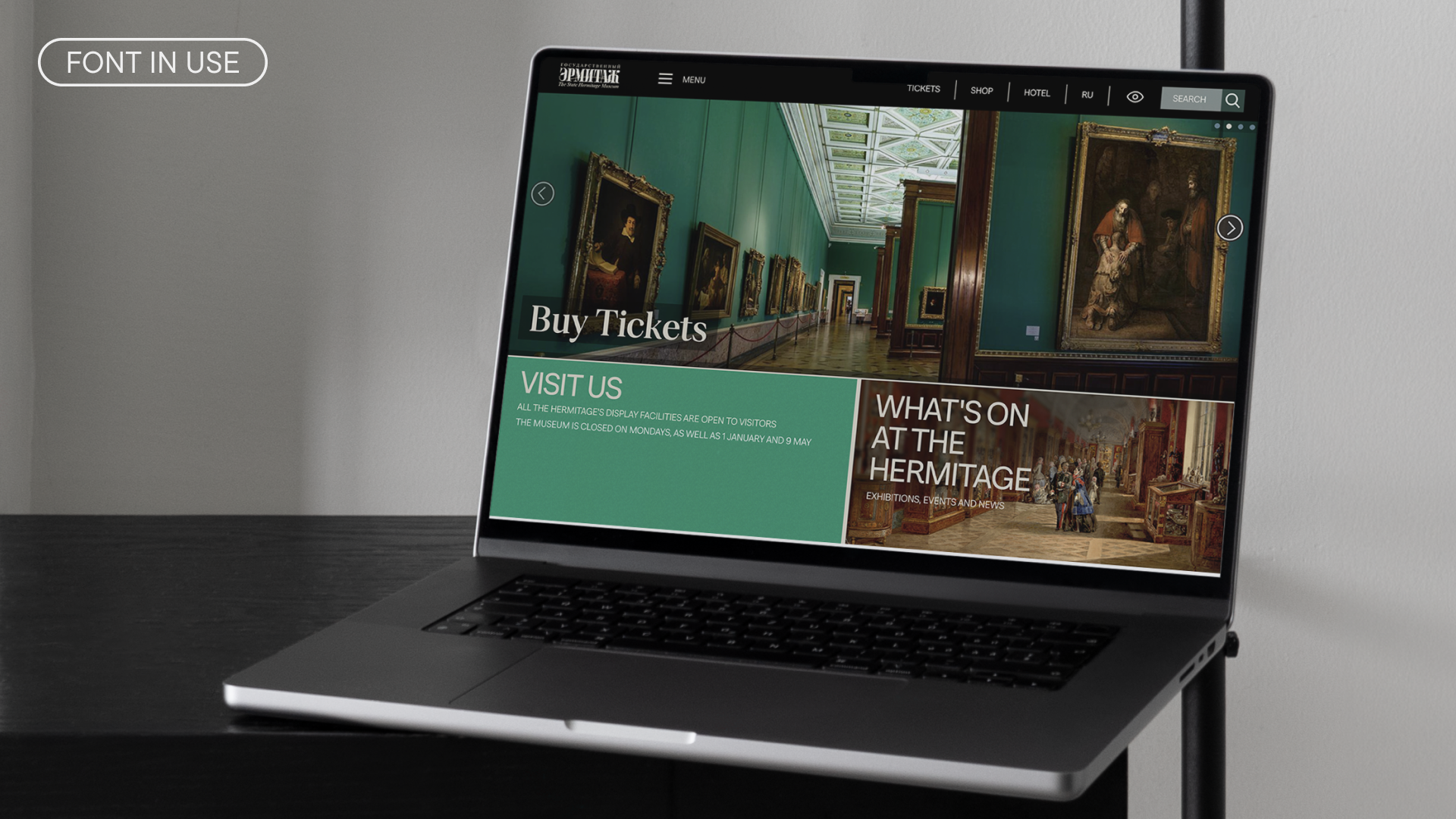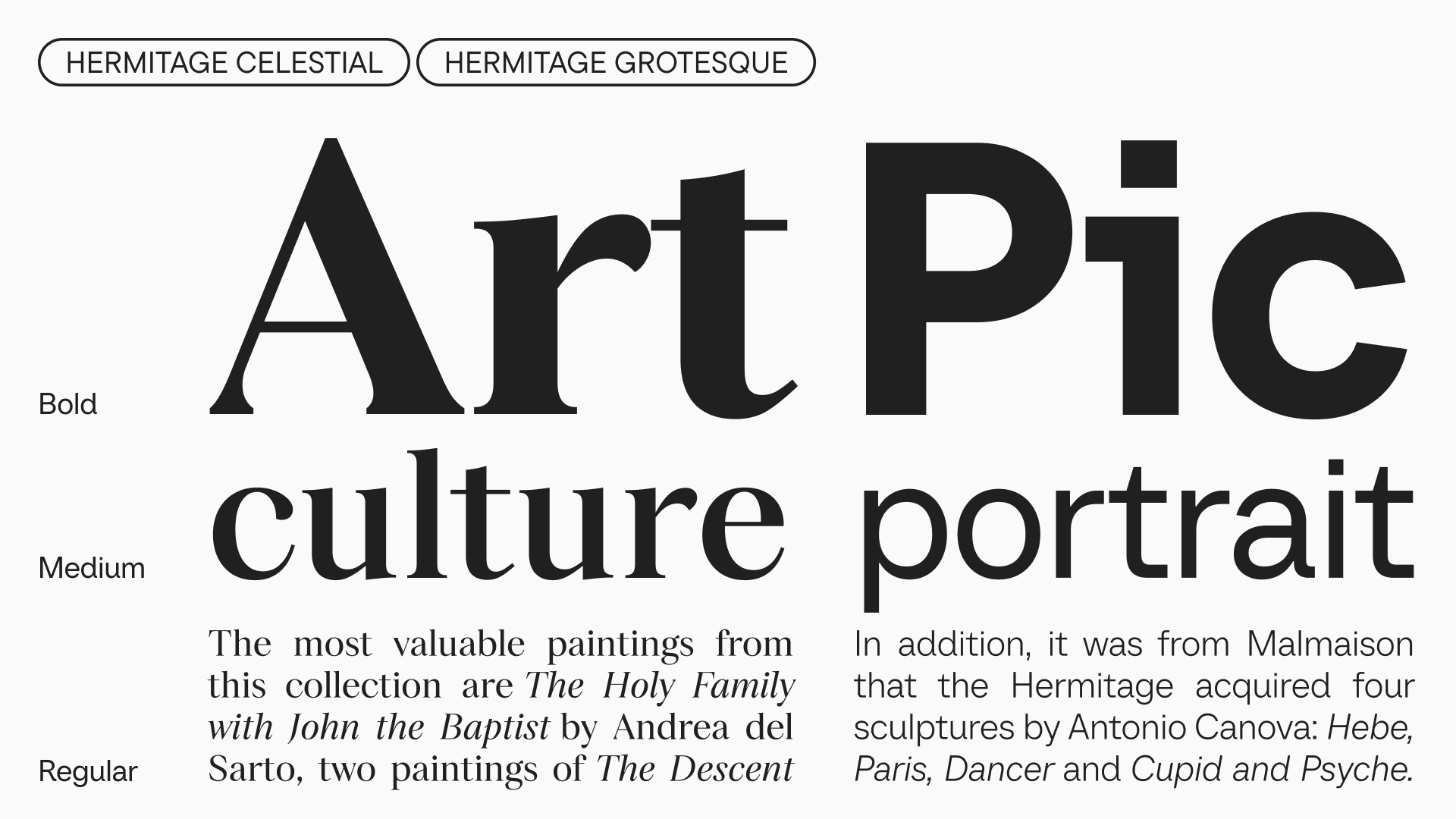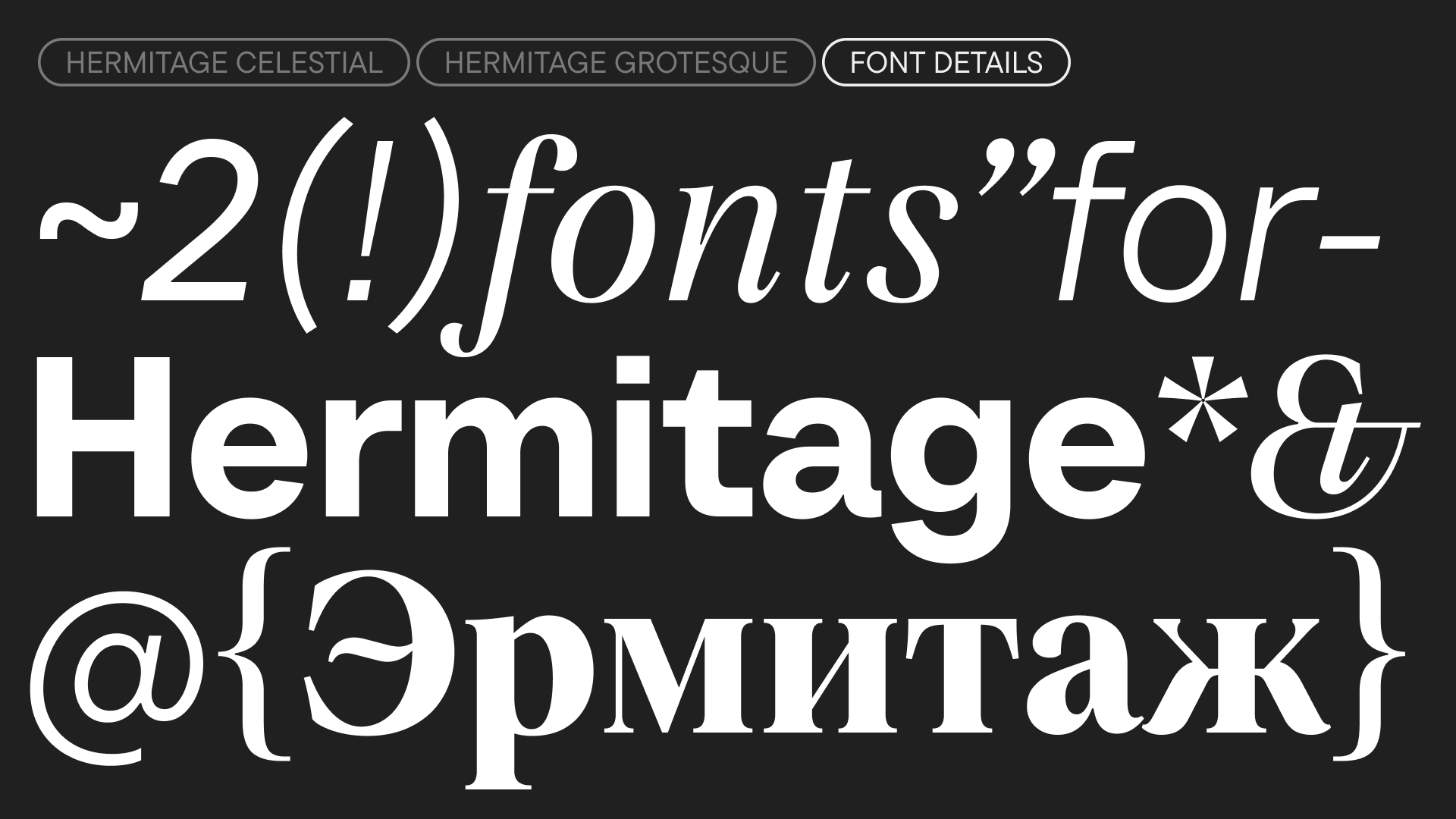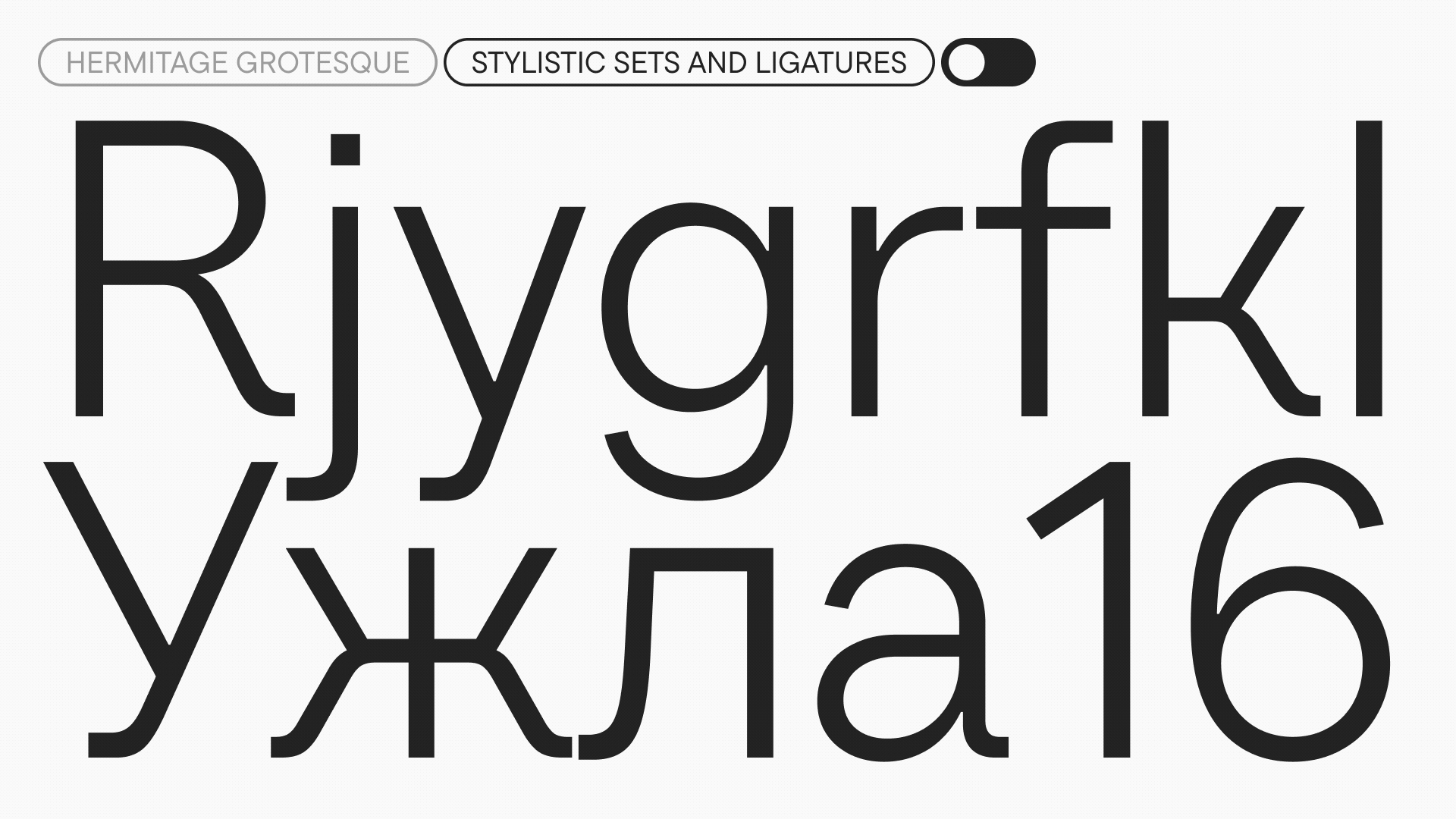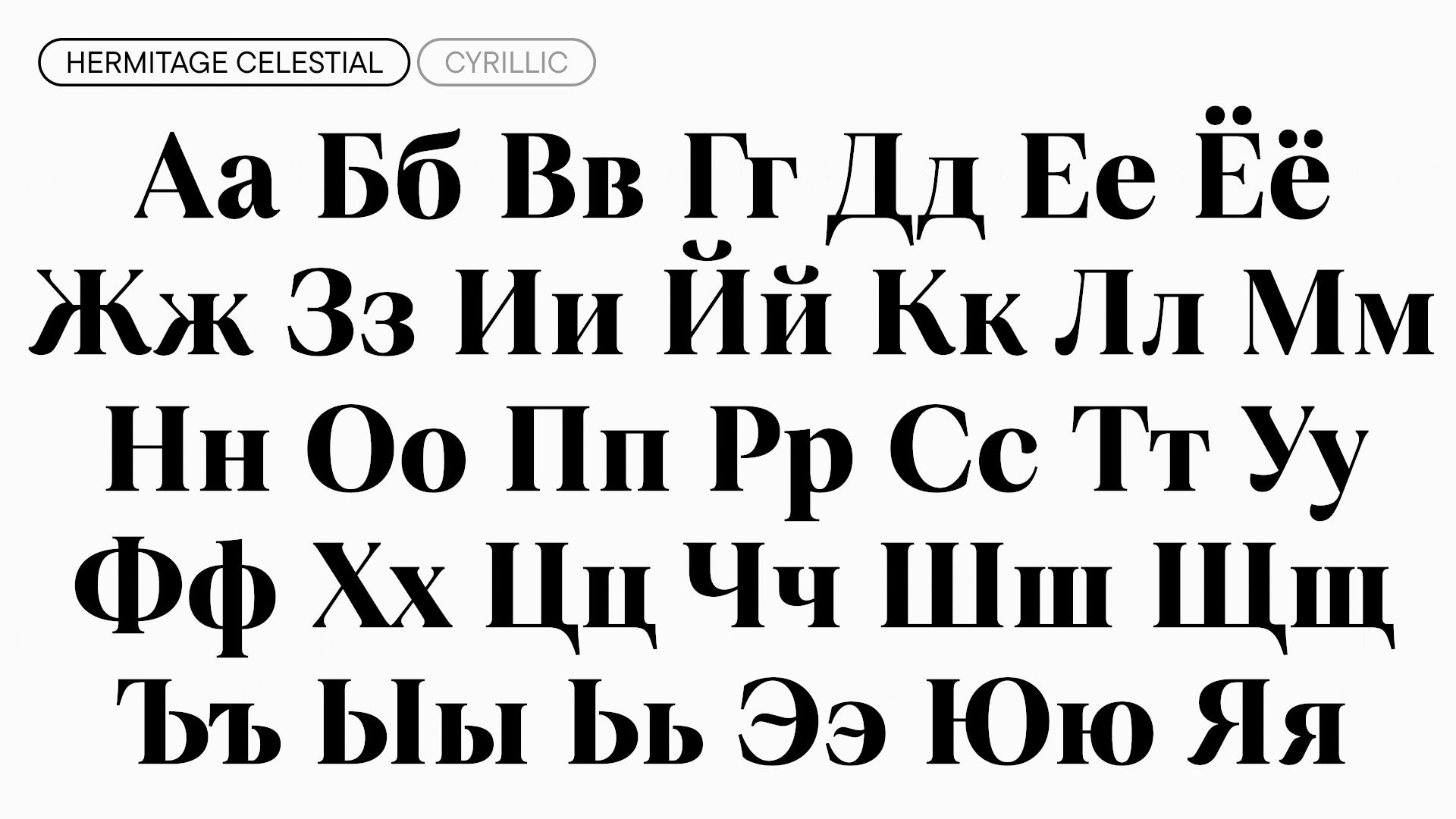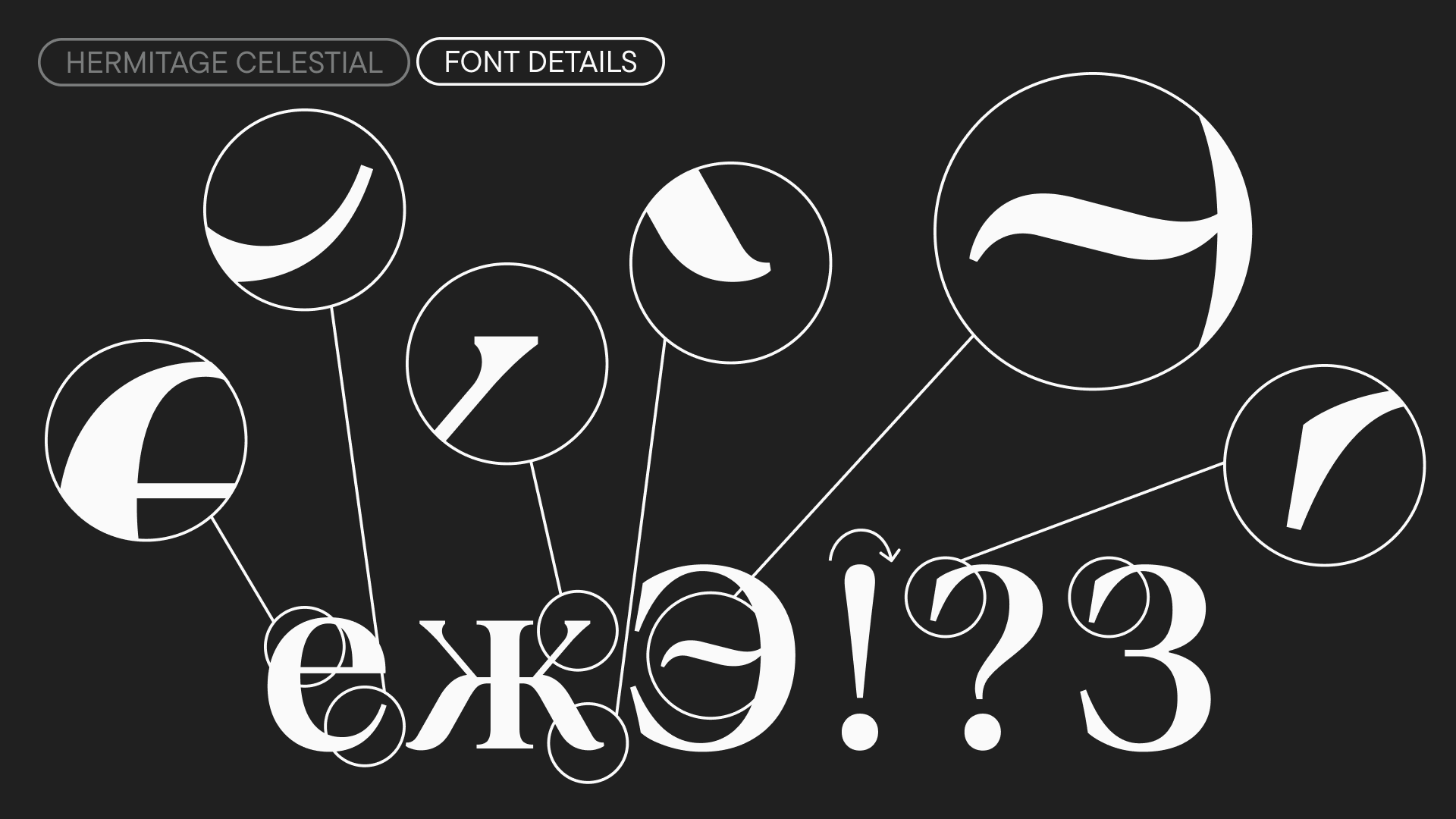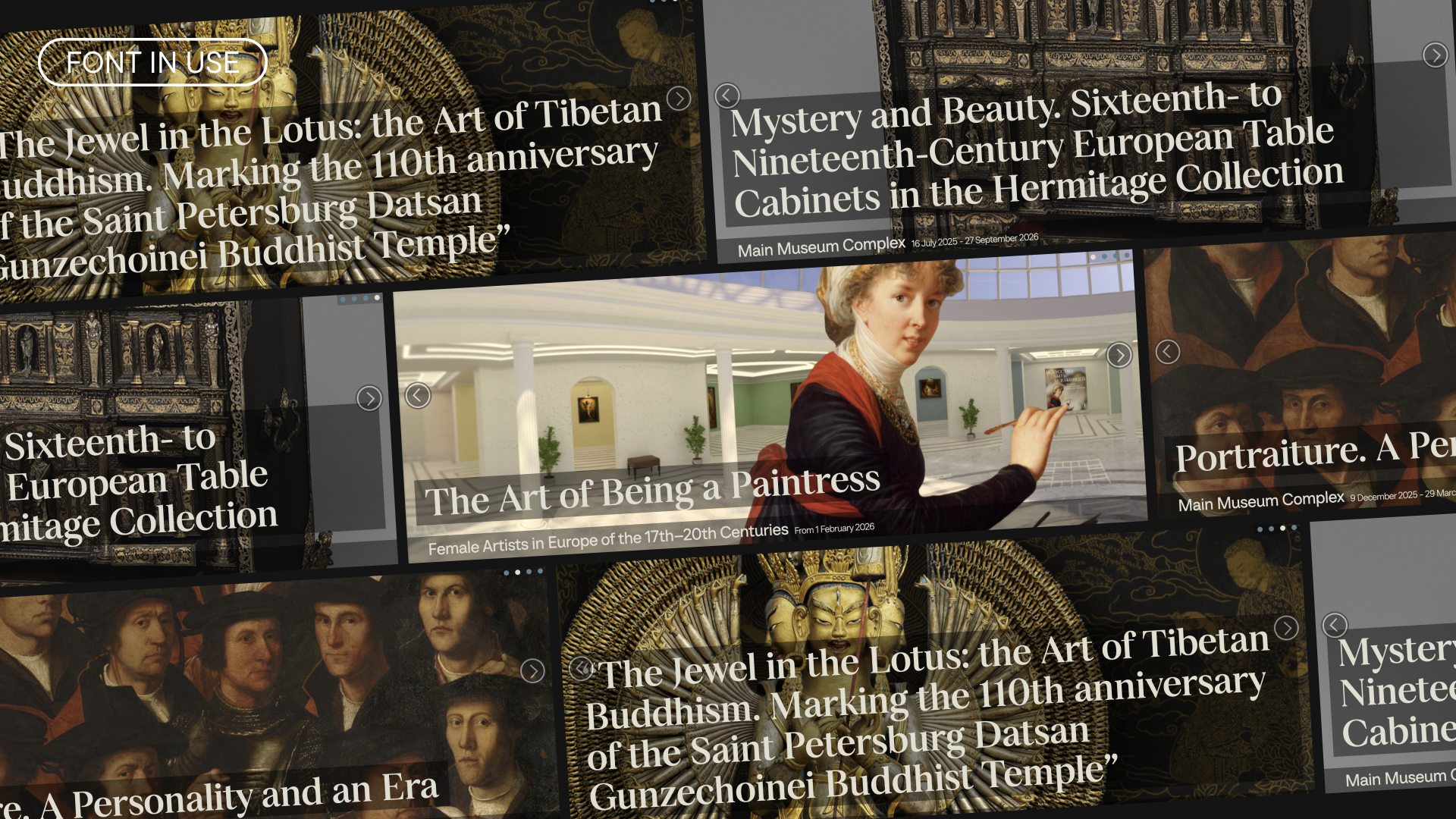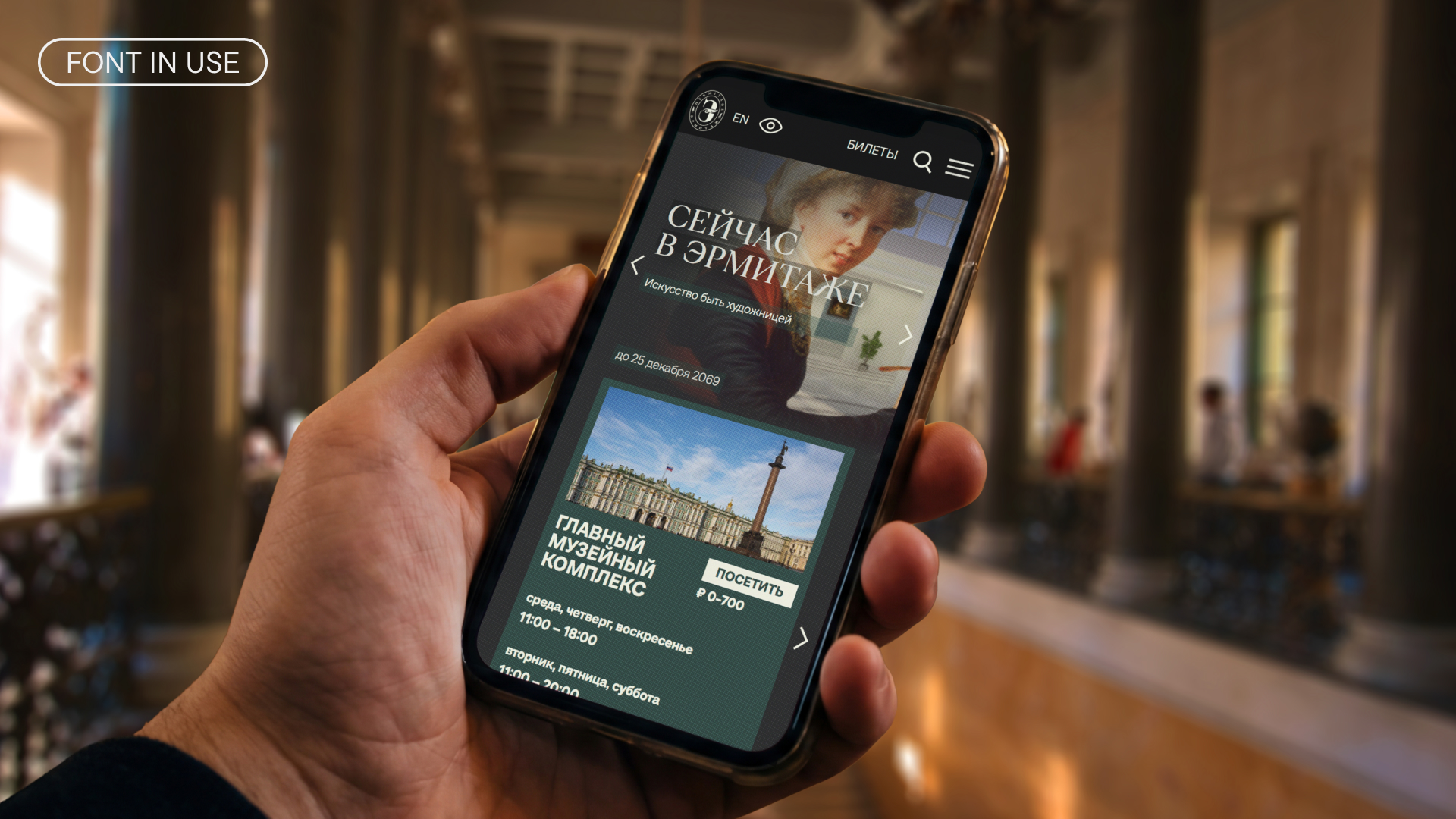
Hermitage Type Family
Hermitage Type Family — новое шрифтовое семейство для Государственного Эрмитажа. Перед TypeType стояла задача разработать такой шрифт, который отразит историю и ценности Эрмитажа, подчеркнёт многогранность его коллекции, и в то же время будет функциональным в использовании. Было важно, чтобы гарнитура подходила для разных задач, разных контекстов и не была стилистически привязана к конкретному историческому периоду.
В основу семейства легли шрифты TT Livret и TT Neoris. Кастомизируя их, дизайнеры студии стремились отталкиваться от логотипа Эрмитажа, но не повторять формы буквально, а сделать мягкое взаимодействие, которое будет считываться интуитивно. В результате получилась функциональная шрифтовая гарнитура, которая объединяет два подсемейства: Hermitage Celestial и Hermitage Grotesque.
Hermitage Celestial — дисплейная антиква для работы в крупном кегле. Её основная задача — отражать ценности Эрмитажа, быть узнаваемой и привлекать внимание. В неё шрифтовые дизайнеры вложили максимум характерных элементов и индивидуальной пластики, объединив современность и бережные отсылки к наследию времён. Шрифт не относится к конкретной эпохе, но его детали раскрываются и звучат по-разному в зависимости от контекста. Сочетание мягких элементов и более холодных, сдержанных решений создаёт большую эмоциональную и графическую вариативность для его применения.
Курсивные начертания добавляют мягкости в характер гарнитуры. Их можно использовать не только для смысловых и контекстных выделений в тексте, но и как полноценный шрифт в небольших текстовых блоках, требующих особого звучания.
Hermitage Grotesque — функциональный гротеск, относящийся к категории интерфейсных шрифтов. Его графика разработана так, что он, с одной стороны, очень хорошо читается в мелком размере, при этом с увеличением кегля раскрывается более детально и приобретает индивидуальность. Характер графики можно значительно менять с помощью стилистических сетов, заложенных в оригинальный шрифт TT Neoris.